Webフォントのデザインテクニック05「混植してみよう」
セルフホスティングの場合、フォントの読み込みには @font-face を使います。そのプロパティである unicode-range を使うことで、フォントの使用する文字範囲を指定できるため、複数書体の混植ができます。
ただし、 unicode-range には、フォントデータをサブセットする機能はなく、表示している文字以外のフォントデータも全てダウンロードされることに注意してください。詳しい仕様は以下のリソースを参照してください。
このプロパティの利用例を2つほど紹介します。
まずは、仮名(句読点を含む)と漢字の混植です。
ひらがなの Unicode 範囲は 3041 – 3096、カタカナは 30A0 – 30FF、句読点は 3001 と 3002 ですので、 unicode-range は以下のようになります。
unicode-range: U+3041-3096, U+30A0-30FF, U+3001-3002;
これを用いて、仮名には濱明朝、漢字にはTPゴシックを用いると、以下のようにアンチック風に組むことができます。
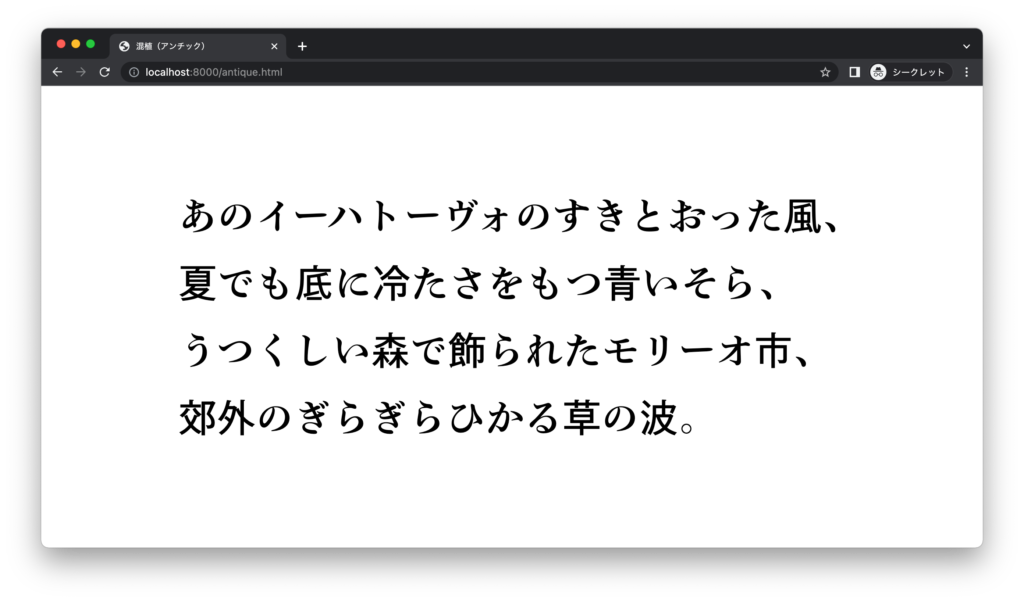
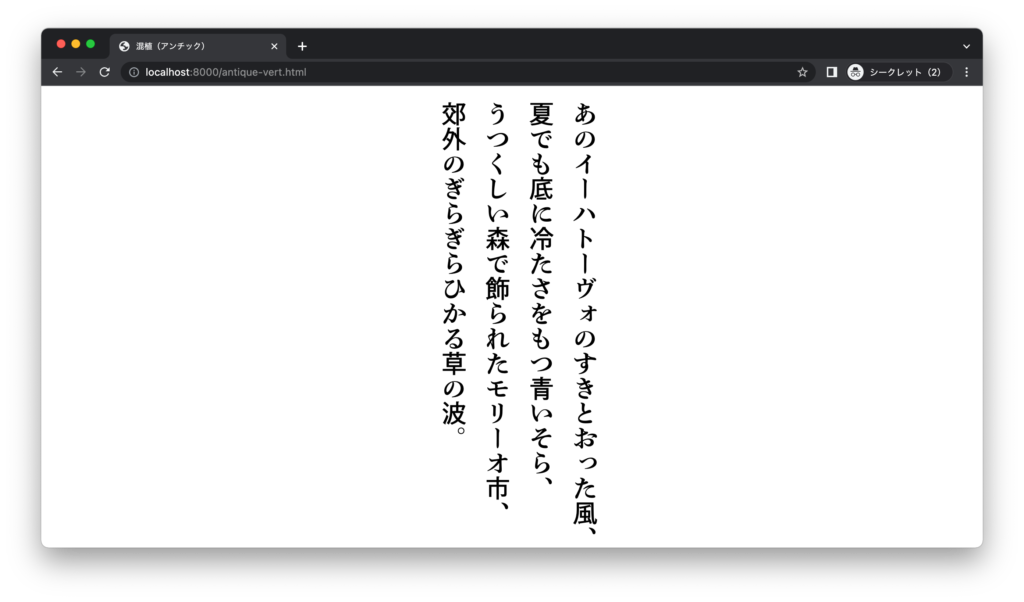
また、見出しでかぎ括弧のみを細くしたいような時にも使えます。
かぎ括弧の Unicode 符号位置は 300C と 300D ですので、 unicode-range は以下のようになります。
unicode-range: U+300C-300D;
これを用いて、AXIS Font ベーシック M の中で、かぎ括弧のみを AXIS Font ベーシック UL にすると、以下のようになります。
(前回の記事の palt も使っています。)
AXIS Font ベーシック M のみで組んだものと比較すると以下のようになります。見出しとして引き締まった印象が出るようになります。
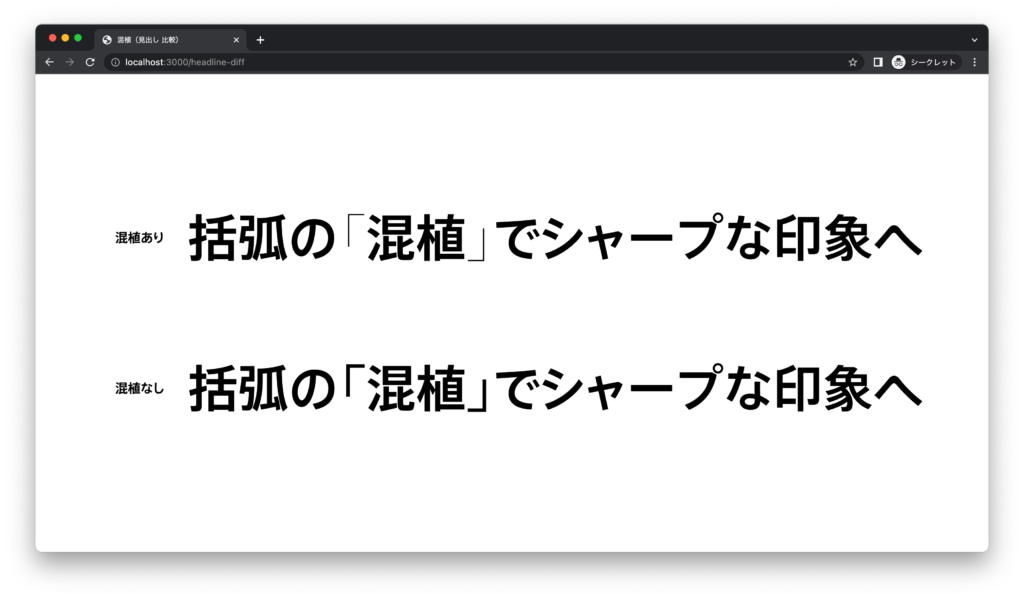
フォントの組み合わせによっては、メトリクスが合わないなどの理由で意図しない表示になることがあるため、注意が必要です。